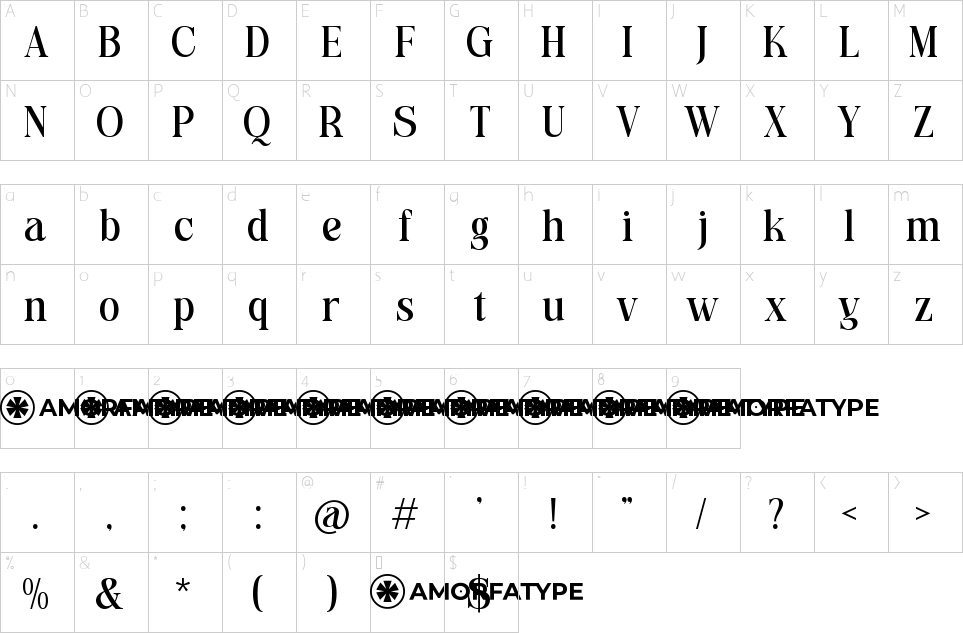
Descubra a elegância e a sofisticação da fonte Mysteris Vintage, perfeita para criar designs que ressoam com o passado sem perder a essência moderna. Desenvolvida pela equipe criativa da Amorfa Type, esta fonte vintage oferece um toque único que se adapta a diversos estilos de design, seja para gráficos de web, design de logotipos ou até mesmo para criação de capas de livros antigos. Com um design detalhado e arredondado, a Mysteris Vintage cria textos que se destacam, deixando um impressionante impacto visual. Seja você um designer gráfico ou amante da arte, esta fonte é uma ótima escolha para incorporar um toque único em seu trabalho. Sua versão gratuita e seu design minimalista torna-a uma ótima opção para iniciantes ou para quem busca uma fonte de qualidade que não compromete a sua criatividade. Experimente hoje e descubra como Mysteris Vintage pode transformar seus projetos.